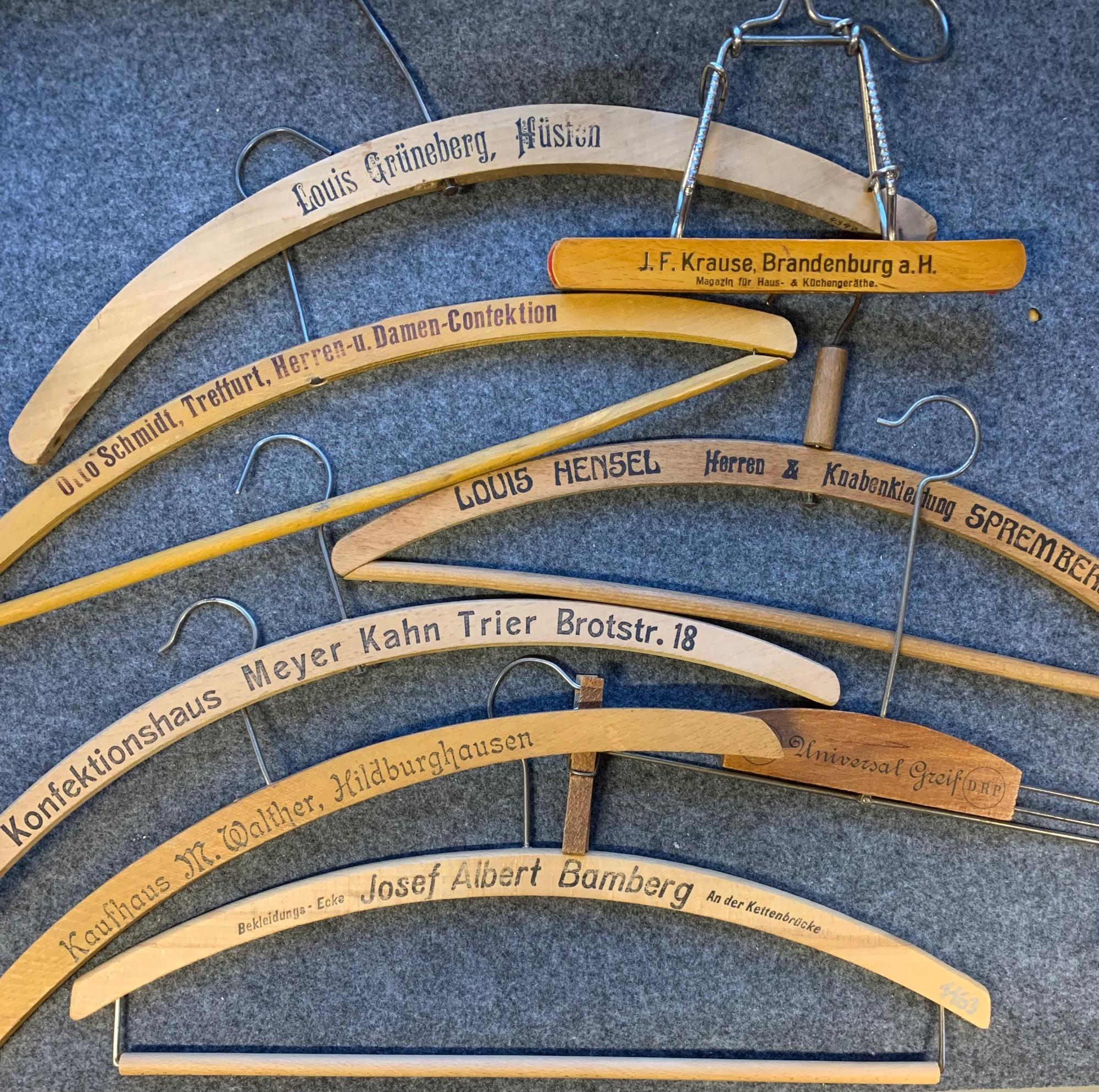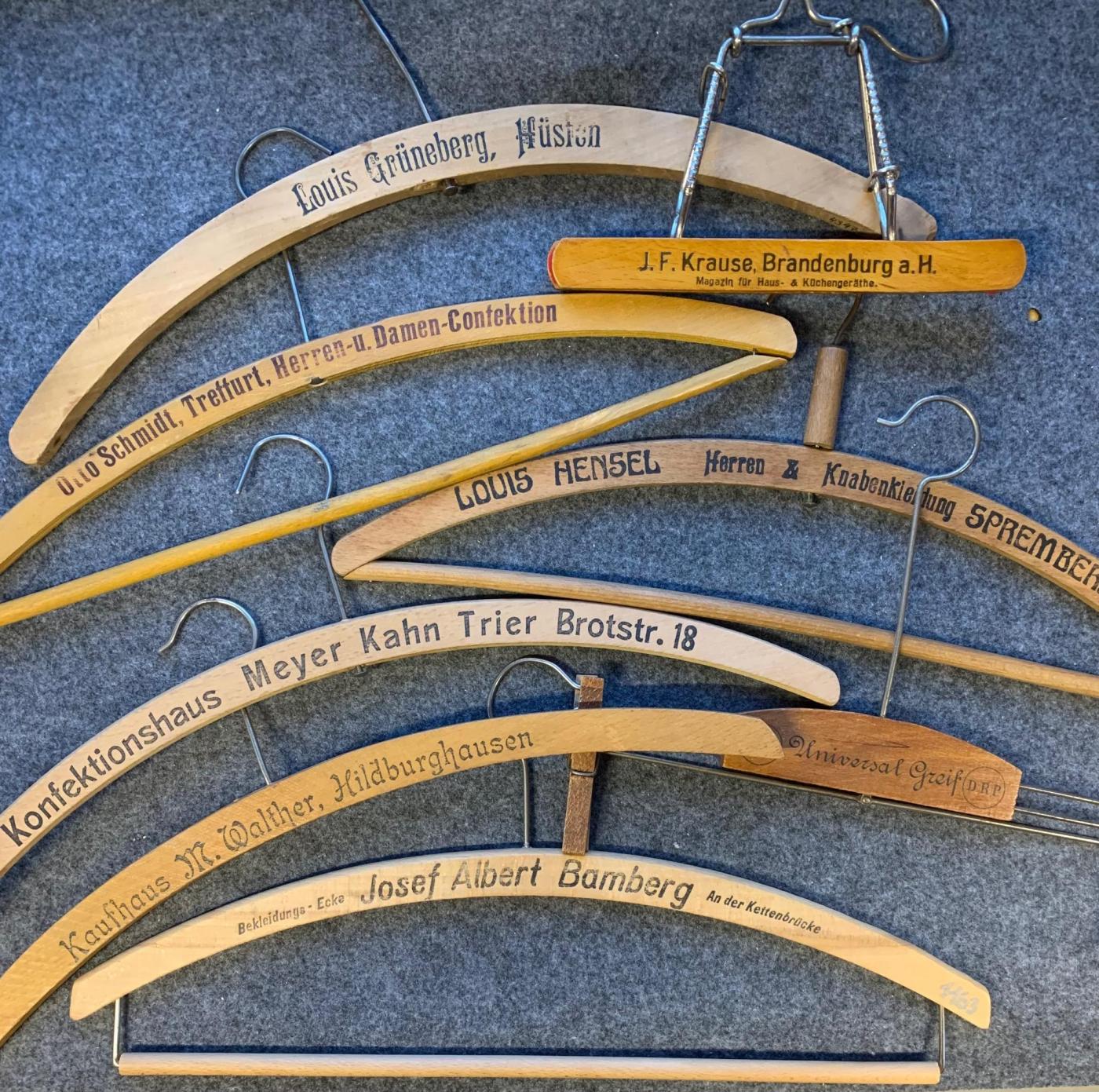
Typographie & Kleiderbügel
Guten Abend, ich bin dieser Gruppe beigetreten in der Hoffnung sie könne mir ein wenig weiterhelfen. Seit vielen Jahren beschäftige ich mich mit dem Thema „Kleiderbügel“ – zugegeben ein auf den ersten Blick etwas abwegig erscheinender Gegenstand der genaueren Betrachtung. Doch bei näherem Hinsehen (und fleißigem Sammeln!), finden sich da so viele interessante Aspekte, dass ich seit gut 20 Jahren „am Bügel“ geblieben bin.
Eine schier unglaubliche Vielfalt von Formen und Funktionen, eine unerwartete Menge Firmen-, Sozial- und Technikgeschichte, viel Erinnerungskultur und seltsame Patente ließen sich hier beispielhaft nennen. Doch um auf den Punkt zu kommen – etwas, was ich im Rahmen meiner Sammeltätigkeit allerdings aufs Heftigste zu vermeiden suche – macht der zumeist einfache, hölzerne Bügel mit einer Aufschrift, neben der sogenannten „Typensammlung“, den allergrößten Teil meiner derzeit etwa 7000 Exemplare umfassenden Sammlung aus.
Die Geschichte des Kleiderbügels verliert sich im Dunkel der Jahrtausende, doch die des modernen Bügels, wie wir ihn kennen, beginnt erst in der 2. Hälfte des 19ten Jahrhunderts, nicht zuletzt als Folge der industriellen Revolution. Nun habe ich mich schon länger gefragt, inwieweit man aus den Schriften brauchbare Hinweise auf das Alter eines Bügels erschließen könnte. Doch wenn ich nur ein wenig in die Literatur sehe, wird mir ganz schwindelig ob der vielen Strömungen ausgerechnet in dem einschlägigen Zeitfenster von, sagen wir von 1890 bis 1980.
Ein erster Schritt könnte vielleicht die Festlegung von „Grundtypen“ sein. Alle Bügel werden in einer Datenbank erfasst, daher könnte ich in das zur Erfassung dienende Formular ein Feld einfügen, das diesen Grundtypus beschreibt. Doch wie gestalte ich das? Jedweder Gedanke wirft für mich erstmal einen Berg neuer Fragen auf.
Bleibt festzustellen, daß ein paar Schriften recht regelmäßig auftauchen, was nicht zuletzt bestimmten Herstellern geschuldet sein mag. Auch könnte ich mir vorstellen, daß ein Produzent, der einen Schriftensatz angeschafft hatte, ihn sicher so lange als möglich in Gebrauch lassen wollte, was wiederum zeitliche Einordnungen ein wenig unsicher macht.
Das angehängte Bildchen möge einen kleinen Eindruck vermitteln, worum es mir geht. Der oberste Bügel sollte schon allein aufgrund der Bauart vor/um 1900 hergestellt worden sein, während der Hersteller des nächsten um 1998 die Produktion begonnen hat und „Küchengeräthe“ noch die Schreibweise vor der II. Orthographischen Konferenz aufweist. Analog läßt die „Confection“ auf dem Bügel aus Treffurt den gleichen Zeitraum vermuten. Bei den nächsten würde ich mich noch nicht wirklich festlegen wollen, doch der letzte dürfte ziemlich sicher, so wie ich, aus den 50er Jahren stammen.
Es würde mich sehr freuen, wenn jemand Ideen zu dieser (noch) vagen Frage hätte!
Das Bild ist leider recht klein und man kann die Details der Schriften kaum erkennen. Für eine genauere Bestimmung wäre ein höher aufgelöstes Bild hilfreich.
Ansonsten kann man über die Schriften eigentlich nur herausfinden von wann der jeweilige Bügel frühestens ist. Wenn eine Schrift beispielsweise 1925 eingeführt wurde kann Sie ab dem Zeitpunkt bis heute eingesetzt worden sein.
Vielen Dank! Bild ist jetzt mit besserer Auflösung eingefügt - es sollte aber nur zur allgemeinen Illustration (im Sinne des "Serviervorschlages" auf Verpackungen ;-)) des Genres dienen. Wichtig wäre mir zu erfahren, nach welchen Kriterien man Schriften im ersten Schritt beschreiben/erfassen/sortieren könnte, um im zweiten Schritt Aussagen zum Alter machen können. Die generelle Altersbestimmung von Bügeln ist ein Kapitel für sich - hier ein paar Merkmale kurz skizziert:
Holzart (auch Material allg.!), Maschinenspuren, Form & Funktion, diverse Ausführungen des Hakens, Firmendaten (manchmal ergibt die Recherche einen sehr kurzen Zeitraum der Existenz = "Leitfossilien", auch Jubiläen), mündliche Angaben (eher unzuverlässig!), Literatur & Kataloge (beides spärlich), Patentschriften,  sonstige Hinweise wie die genannte Rechtschreibung, aber auch die Warenzeichen (DRGM u.ä.), Hinweise wie Postleitzahlen (2-stellig, 3-stellig usw.), DDR Kennzeichnungen (EVP etc.) ...
die Schriften sind natürlich auch ein wichtiges Merkmal, dem ich in Zukunft etwas fundierter gerecht werden möchte ...